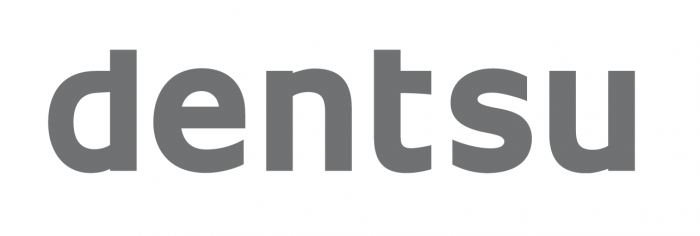
dentsu Schriftart gesucht!
Hallo zusammen, ich bin auf der Suche nach der dentsu Schrift.
Mir ist schon klar das es ein Logo ist aber die Ursprungsschrift kommt mir so bekannt vor.
Da wurden ja eigentlich "nur" die Buchstaben beschnitten.
Dass die weltgrößte Werbeagentur eine Satzschrift nimmt und nur die Buchstaben beschneidet, kann ich mir nur schwer vorstellen.
Zumal 5 Buchstaben zu zeichnen, und einen davon noch mal auf den Kopf zu stellen schneller erledigt ist (und dabei zu einem individuelleren Ergebnis führt) als sich erst vauf die Suche nach einer passenden Schrift zu machen, der man dann die Oberlängen kappt und eventuell noch gründlich dran herum zupfen muss.